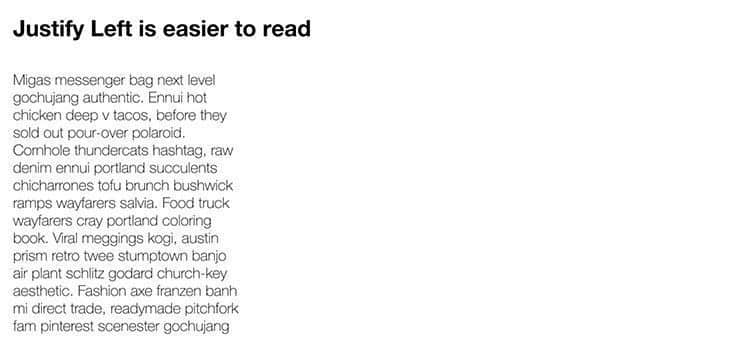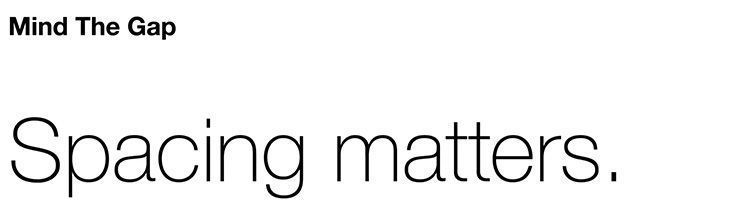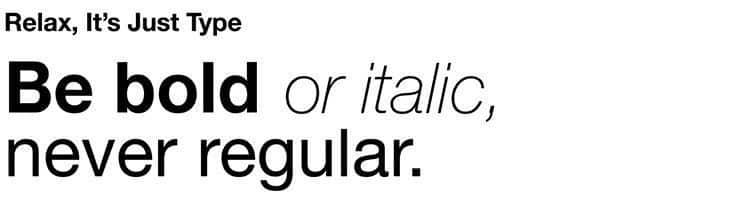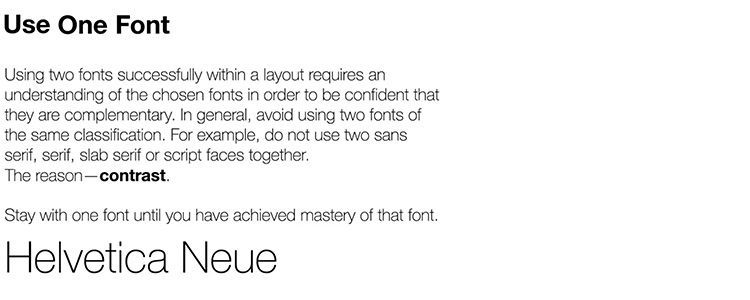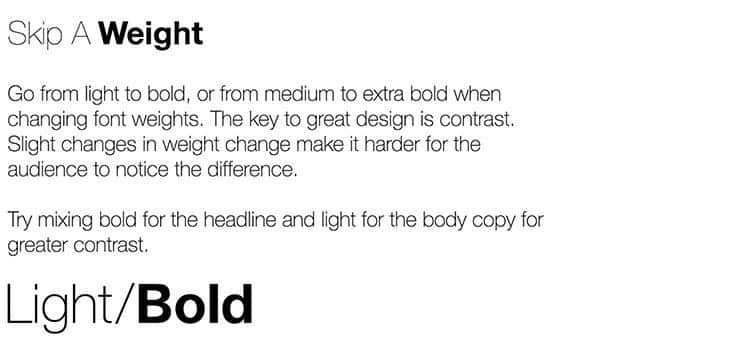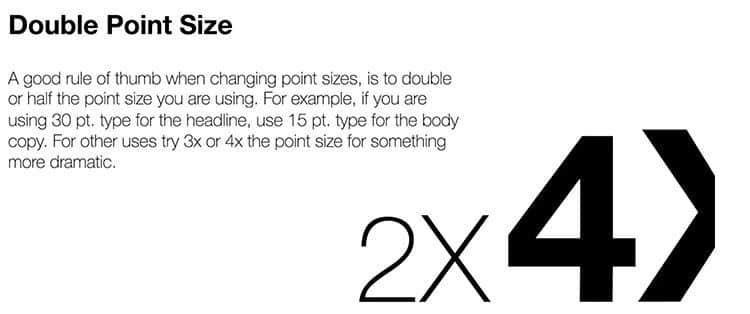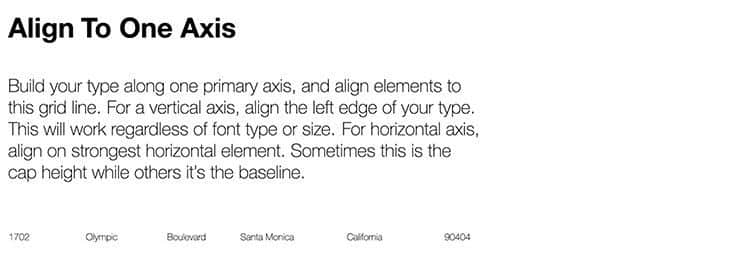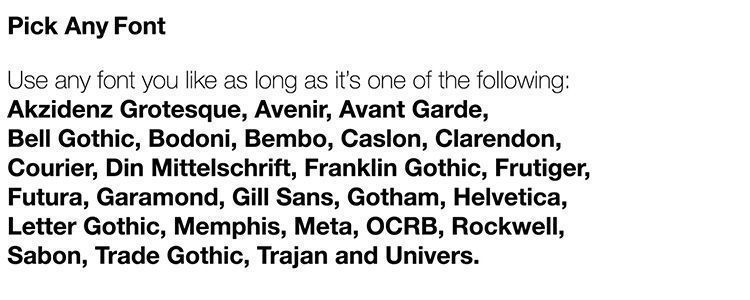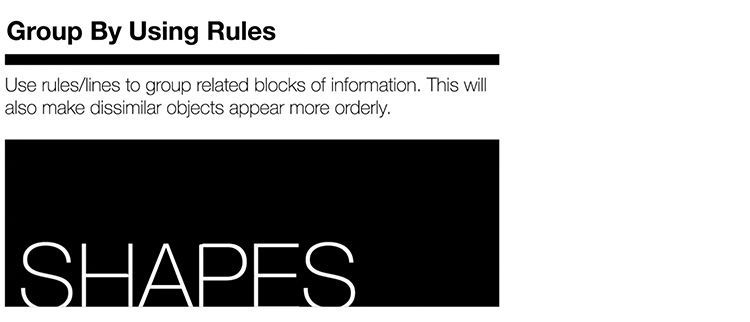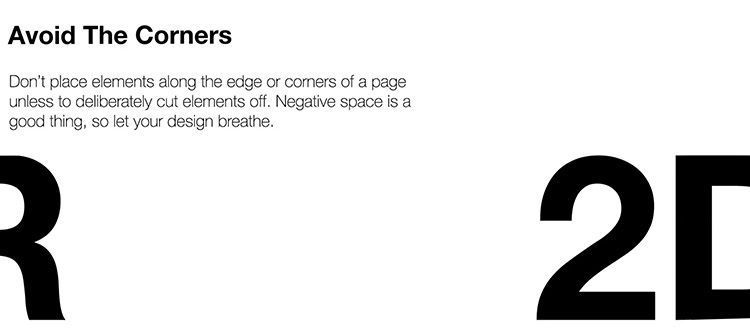
Las 10 reglas de la tipografía resumidas en un genial vídeo
10 reglas básicas de la tipografía
Las 10 reglas de la tipografía básicas resumidas en un genial video de 3 minutos.
Los profesionales del mundo del diseño y la publicidad tendemos a olvidar las nociones básicas de los conceptos aprendidos. La vorágine diaria y la necesidad de innovar constantemente para sorprender a los consumidores hacen que obviemos las reglas básicas de la tipografía y el diseño. A veces, un ‘Back to the Basics’ pueden salvarnos de un mal día componiendo piezas.
Para ello nos hacemos eco del excelente vídeo que han creado en The Futur, donde tratan de forma animada 10 reglas de la tipografía para aplicar en nuestros trabajos. Un vídeo imprescindible para tener frescas estas reglas para todos aquellos que estén empezando a formarse como diseñadores y los profesionales que necesitan recordar las reglas de la tipografía.
1.- Justifica a la izquierda
En caso de duda, siempre justifica a la izquierda, solo en alguna excepciones a la derecha (sobretodo para alinear cifras de moneda), pero nunca fuerces la justificación (algo bastante común en las columnas de los periódicos pero crea «ríos» de bloques de texto extrañamente espaciados). La razón por la que debes justificar la tipografía a la izquierda es porque es más fácil de leer. Los bordes izquierdos hacen que el comienzo de los párrafos sea más fácil de encontrar. Por esa razón, también es preferible no sangrar la primera línea de un párrafo.
2.- Usa un tipo de fuente
Cuando empieces a diseñar, mejor hazlo con solo una fuente hasta que domines los fundamentos de la tipografía. Reducir el número de opciones te permitirá centrarte en hacer un buen diseño. Para utilizar dos fuentes tipográficas es necesario un entendimiento de las fuentes elegidas y saber si son complementarias o no. En general intenta evitar usar dos fuentes de la misma clasificación, no uses dos serif, sans serif o manuscrita juntas.
3.- Grosor de las fuentes
Ves de Light a Bold, o de Medium a Extra Bold cuando cambies el grosor de las fuentes. La clave es el contraste ya que pequeños cambios de grosor puede hacer que el lector no note los cambios y se pierda el efecto que quieres conseguir.
4.- Doblar el tamaño
Una buena regla para cambiar de tamaño de fuente es doblar (o dividir) la que esté usando en un inicio. Por ejemplo, si estas utilizando 30 pts. para un titular, utiliza 15 pts. para el texto del cuerpo. Otra de las opciones para ganar notoriedad es ampliar x4 la fuente inicial.
5.- Alinear a un eje
A la hora de construir tu diseño hazlo sobre un eje primario y alinea los elementos a esa línea de cuadrícula. Para un eje vertical, alinea al borde izquierdo de la tipografia, eso funcionará independientemente del tipo o tamaño de fuente. Para un eje horizontal alinea la fuente al elemento central más destacado, puede ser la altura de la tapa o a veces la línea de la base.
6.- Escoge cualquier fuente…
Utiliza cualquier fuente que te guste, siempre que sea una de las siguientes: Akzidenz Grotesque, Avenir, Avant Garde, Bell Gothis, Bodoni, Bembo, Caslon, Clarendon. Coureri, Din Mittelschrift, Franklin Gothic, Frutiger, Futura, Garamond, Gill Sans, Gotham, Helvetica, Letter Gothic, Memphis, Meta, OCRB, Rockwell, Sabon, Trade Gothic, Trajan and Univers.
7.- Agrupa utilizando reglas
Usa las mismas reglas para agrupar bloques de información, esto hará que los objetos más diferentes parezcan más ordenados.
8.- Evita las esquinas
No coloques elementos en las esquinas de la página a menos que los cortes deliberadamente. El espacio negativo es bueno para que tu composición respire.
9.- Cuida la composición
En la tipografía el espacio lo es todo. No justifiques porque se crean bloques de espaciado dentro del texto. Evita también el ‘efecto viuda’, que es dejar una palabra sola en la última línea de parágrafo. Tampoco empieces una página o parágrafo con la última línea del parágrafo anterior. Cuida el espaciado, cuanto más cerca estén las palabras, más le costará al lector entender la composición.
10.- No te agobies, solo es tipografía
Juega, experimenta, practica, observa, aprende, evoluciona. Es solo tipografía, no te desesperes. Todo el mundo tiene un estilo para aplicar y no todas las composiciones se van a parecer, en caso de duda, vuelve a los orígenes con estos pequeños consejos y vuelve a arrancar.